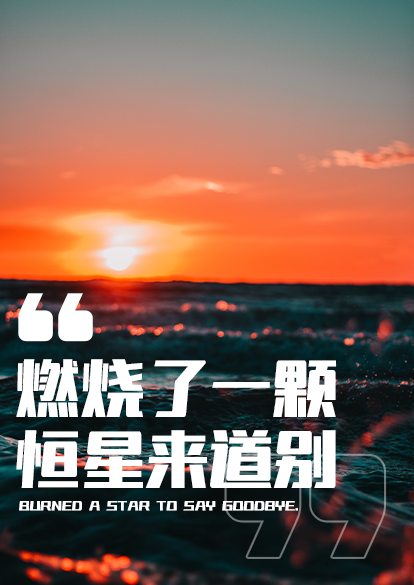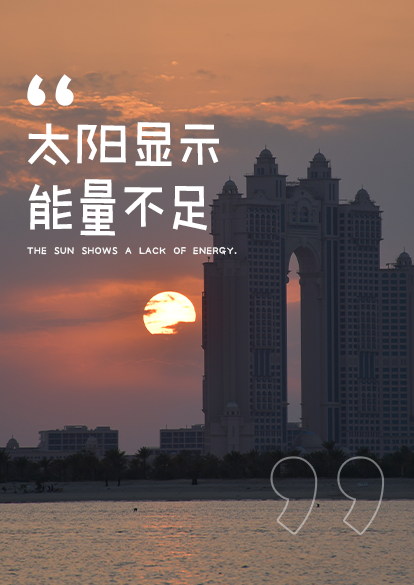
设计师必看的情绪字体与排版指南!
情绪是Z时代的指向标,越来越内卷的市场、越来越个性化的需求,Z时代更倾向于表达情绪、传达个性的独特字体。
励字造梦共创字库,根据字体的情感化表达,把汉字作为语言符号在象形表意的功能基础上,传达文字信息时表现出的感情色彩。
1:磅礴大气的情绪表达
励字磅礴简 高,横看成岭侧成峰,“磅礴黑”实验性地采用斜体与正体的融合,左侧倾斜的手法在整体稳重大气的字形中增添少许灵动,右侧的垂直设计支撑起整个架构,形成“气势磅礴,万壑争流”之势,不禁感叹“不识庐山真面目,只缘身在此山中”。
2:可爱情绪
励字可变敲可爱简,一款略带俏皮,充满趣味与想象的创意直线字。手写的圆润线条在保留辨识度的前提下,省略部分笔画,简单,明快的线条,独特的形式,营造用心书写的随性,让字体更具手绘感,带来手写的柔软和温暖。